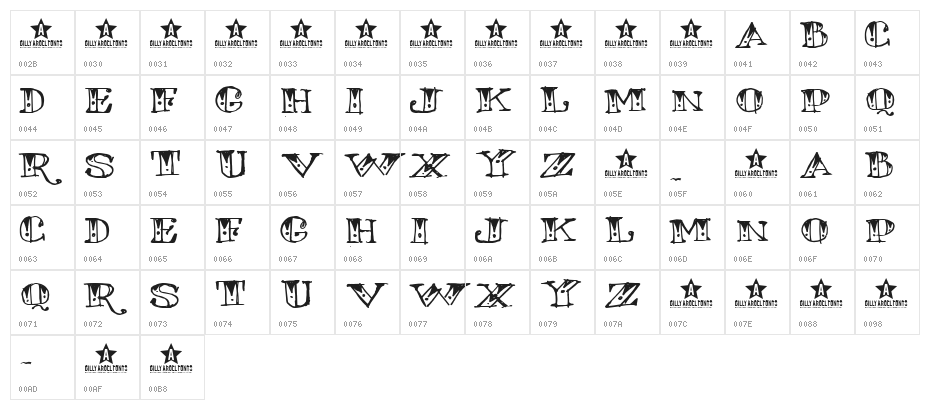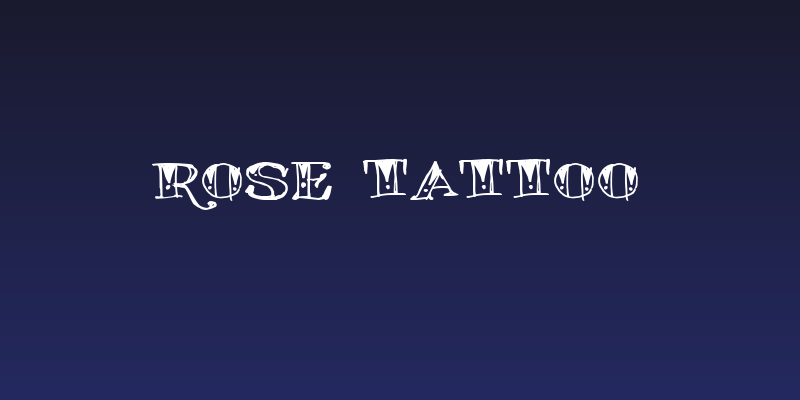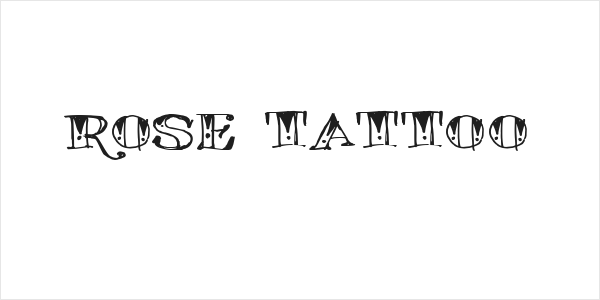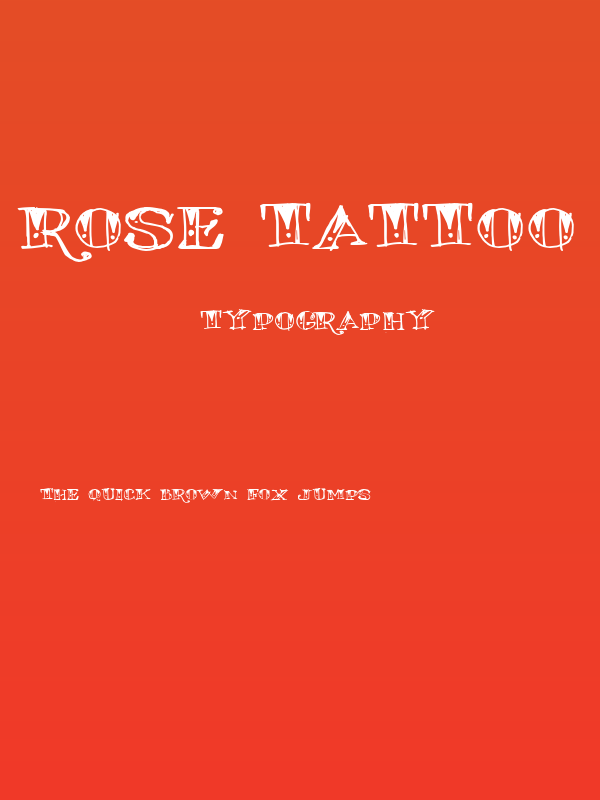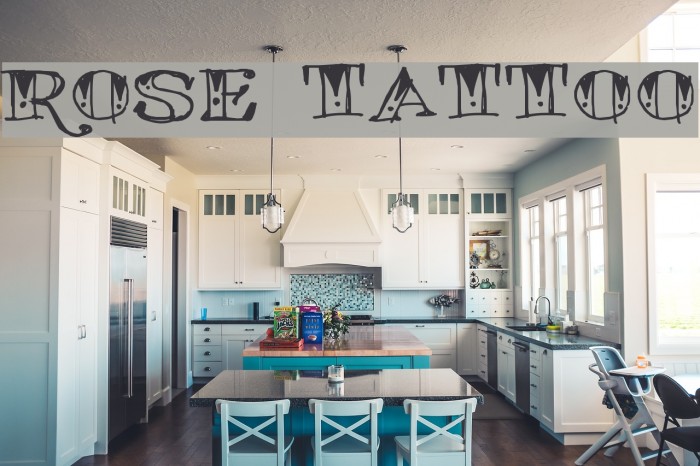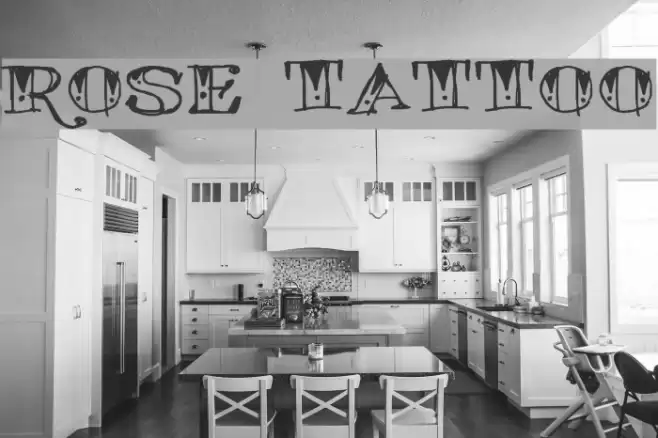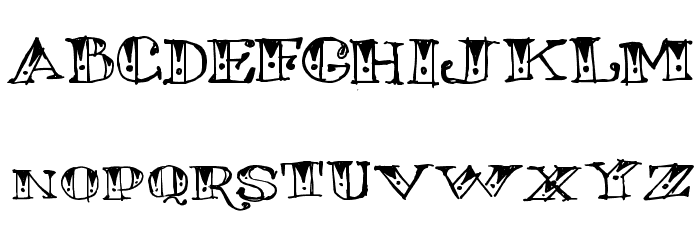
ROSE TATTOO Font
| Anwendungsfall | Logos, Headlines, Posters |
| Vorgeschlagene Projekte | Ideal for tattoo designs, album covers, posters, and branding that requires a bold, artistic touch. |